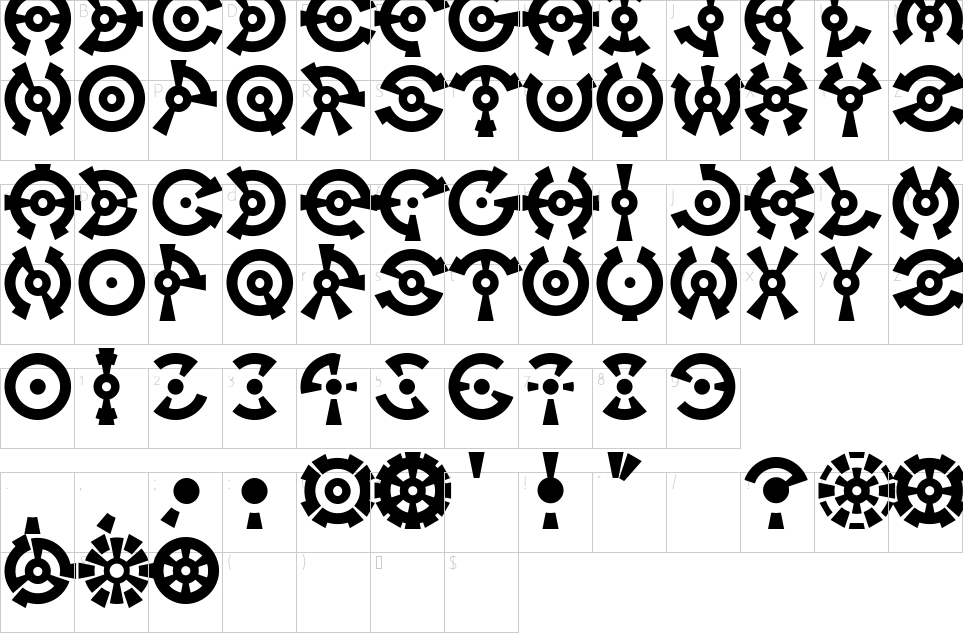
Anillo é uma elegante fonte gráfica que se destaca pela sua elegância e simplicidade. Inspirada na arquitetura e na geometria, Anillo é uma escolha ideal para criar designs que se destacam, seja em elementos de marca, materiais de design gráfico ou em elementos digitais. Esta fonte foi criada pelo designer Iconian Fonts e oferece uma variedade de opções de estilo que vão desde linhas levemente curvas até texturas mais sofisticadas. Com sua utilização em projetos digitais e impressos, a Anillo se destaca como uma fonte versátil e de alto desempenho. Download a sua agora e adicione uma pontada de sofisticação a seus projetos.